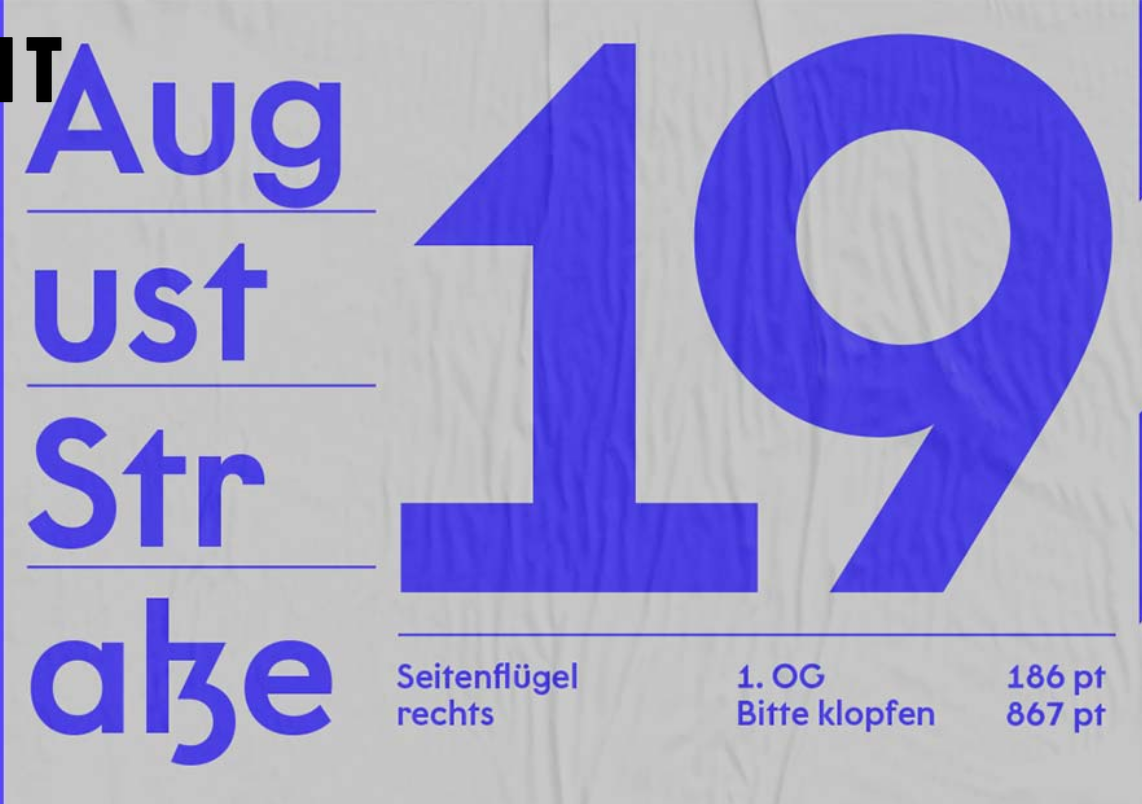
Suche Schriften mit alternativer fz Ligatur.
ich bin über die LitSans gestolpert. Eine schöne Sans-Serif mit dem wunderbaren Alternativ-ß, also der historischen fz-Ligatur mit Unterschlinge „ʒ“.
und nun hab ich mich gefragt, wie ich wohl an eine Auswahl komme von Schriften die genau diese Alternativen besitzen. Vielleicht gibt es sowas sogar auf dem Sektor, beachtenswerter Freefonts, oder sowas.
Nun suche ich weitere Schriften auch andererer Klasssifizierungen
- FF Cst Berlin
jemand Ideen zur vervollständigung dieser Liste, gerne mit Links.